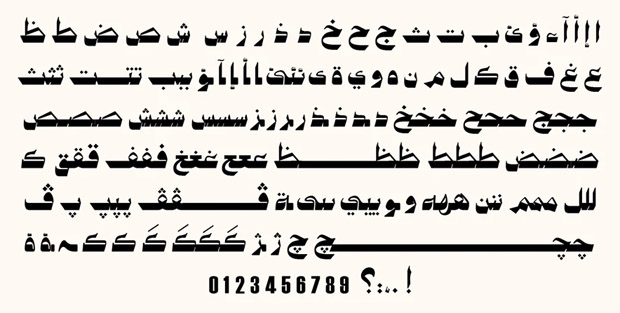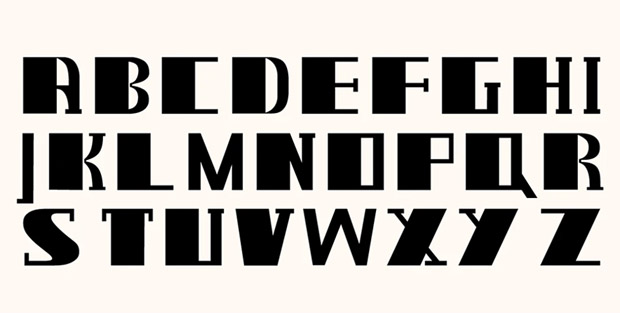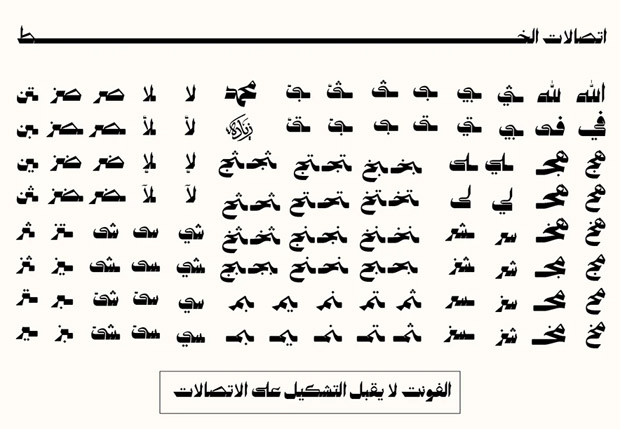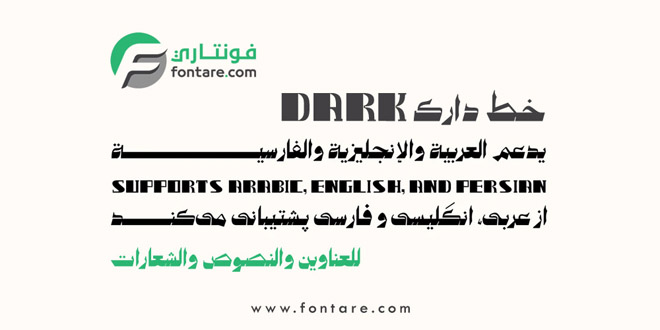
خط دارك السميك للعناوين والنصوص والشعارات عربي إنجليزي فارسي
خط دارك السميك للعناوين والنصوص والشعارات عربي إنجليزي فارسي .. هذا الخط متغير معاصر يهدف إلى توحيد العربية والإنجليزية والفارسية في نظام بصري واحد، تصميم موحّد يجعل الحروف من هذه اللغات تتناغم ضمن نفس العائلة دون اختلافات بصريّة مزعجة، مناسب للتصميمات الحديثة والعلامات التجارية التي تتطلب دعم نصوص متعددة.